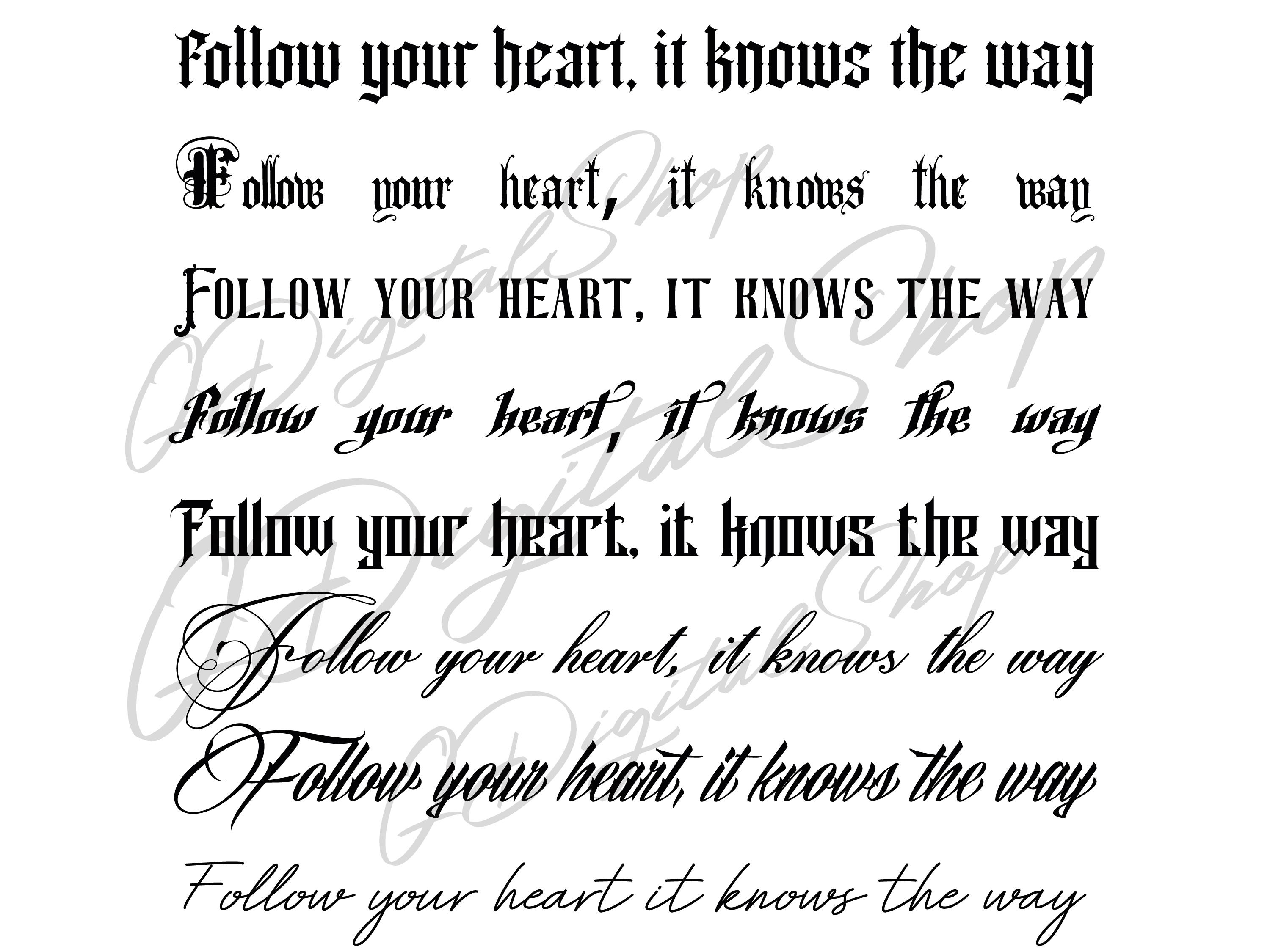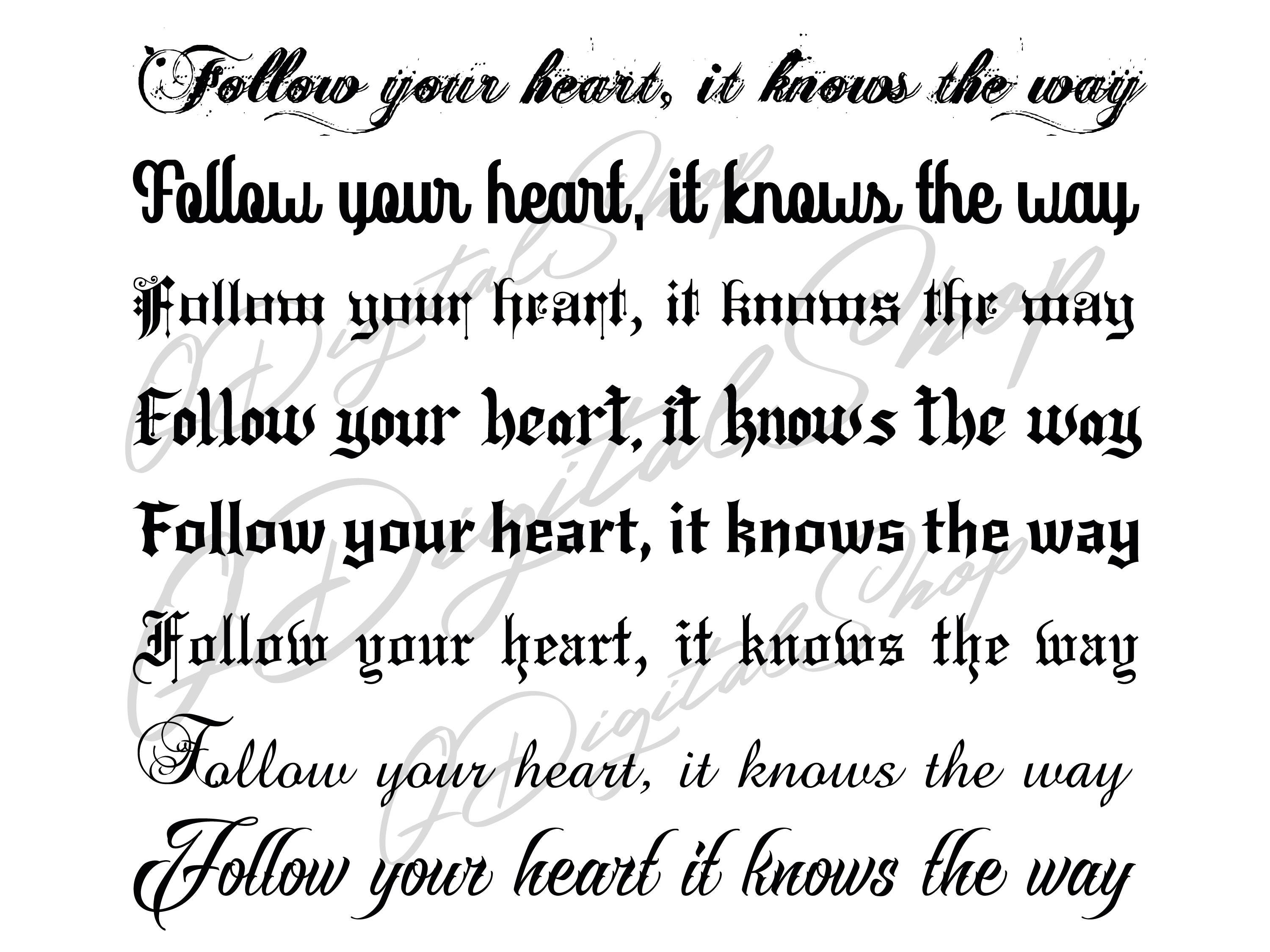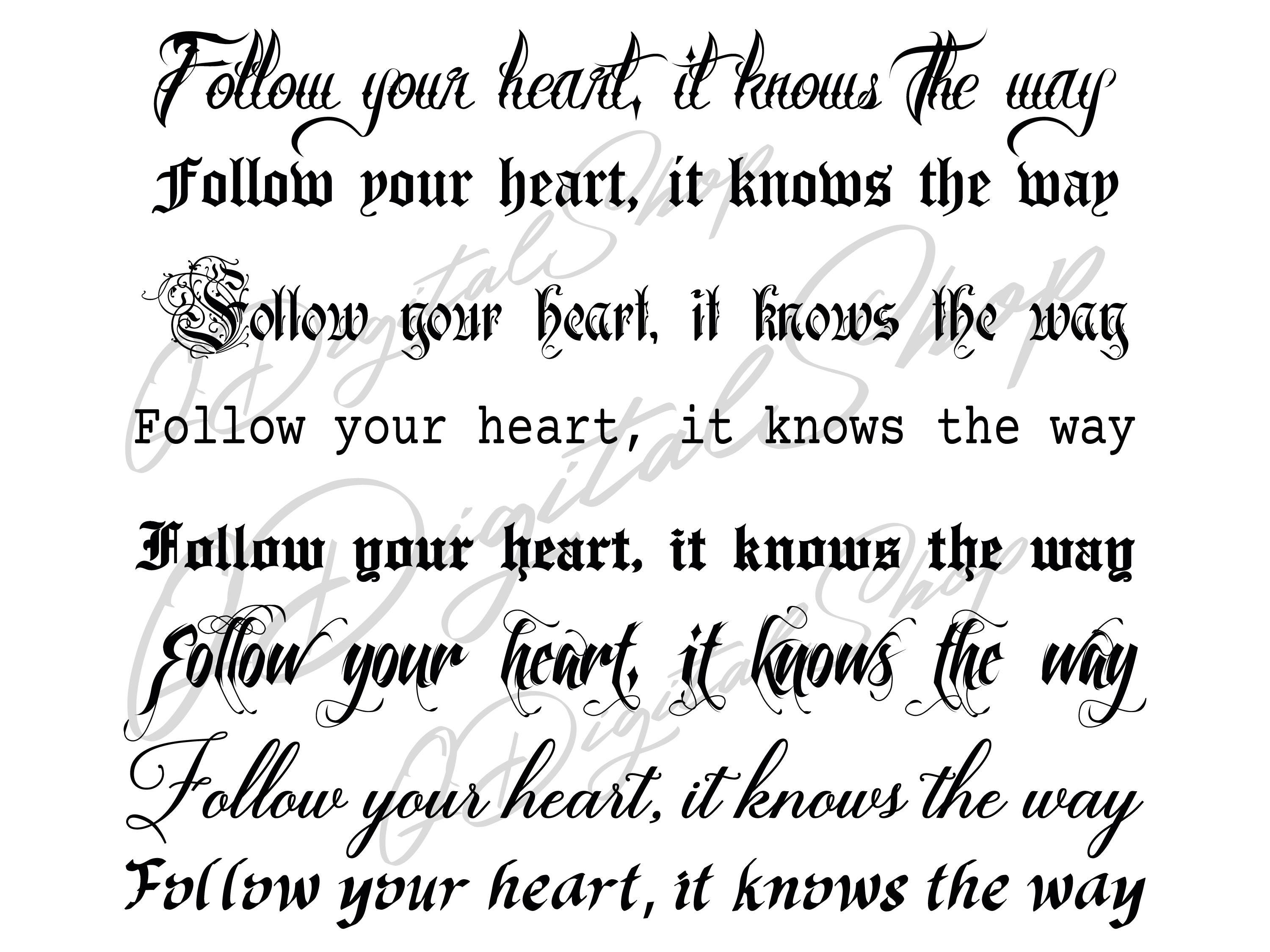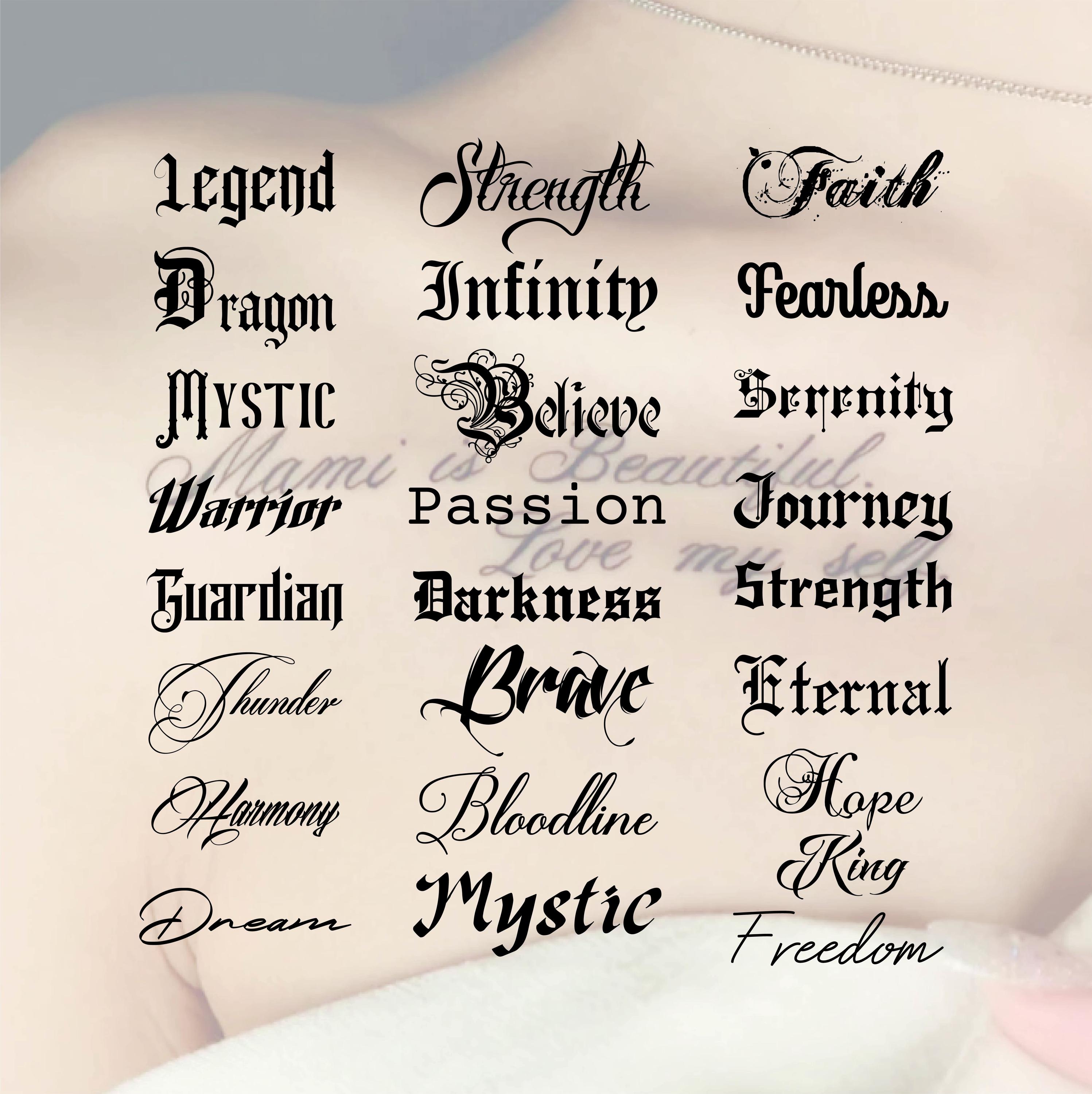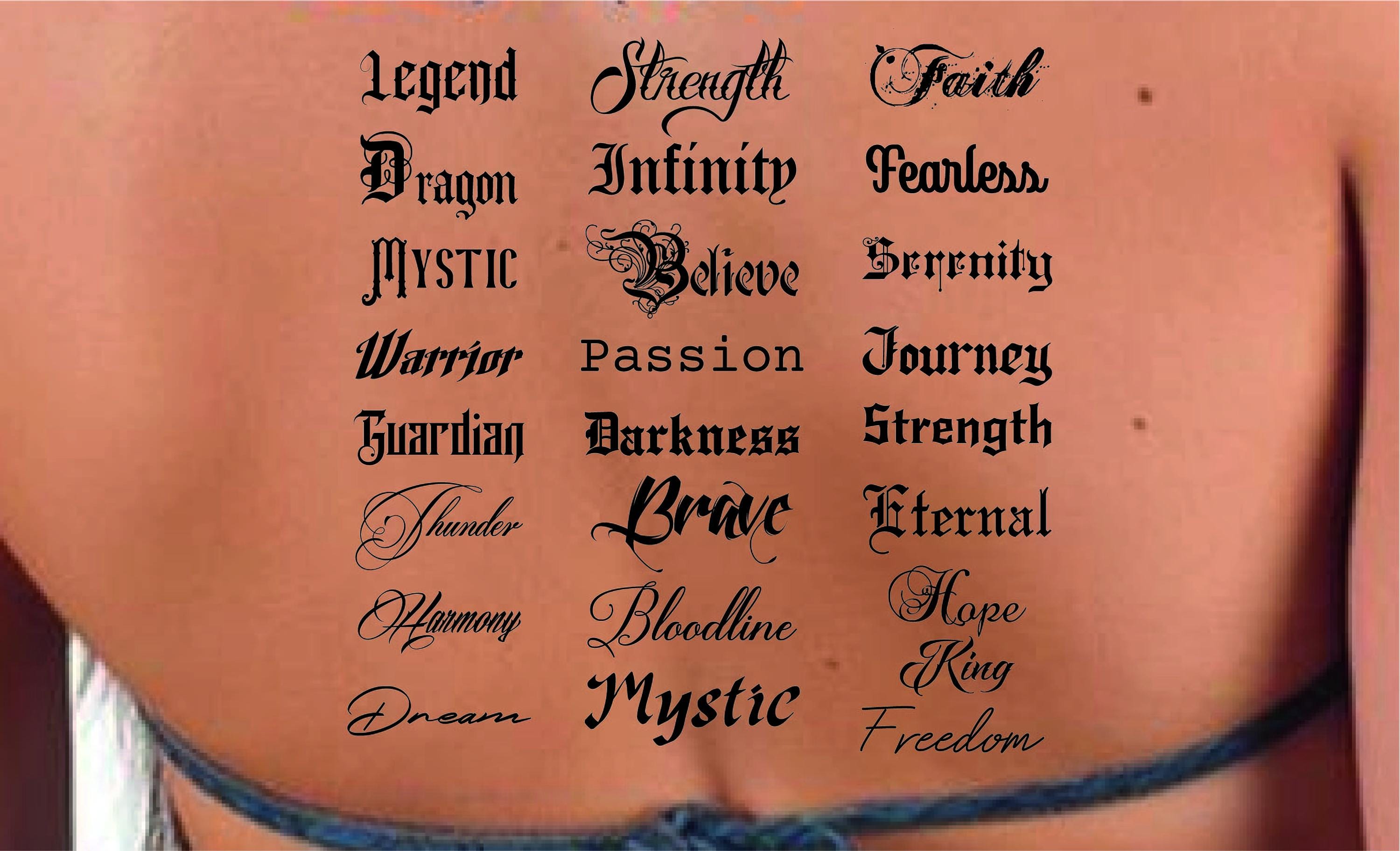
プレミアムタトゥーフォントバンドルで作品をグレードアップ。大胆なクリエイター、タトゥーアーティスト、メーカーのために厳選した、プロ品質のタトゥーフォント24種を収録。クラシックなスクリプトやカリグラフィーから、エッジの効いたモダンレタリングまで、デジタル/フィジカル問わず多彩なプロジェクトで魅力的なデザインを生み出せます。タトゥーフラッシュ、アパレルグラフィック、Cricut用デカール、SNS投稿、ポスター、招待状、ウォールアートなど、いつでもシャープで高品質な仕上がりに。
- プレミアムタトゥーフォント24種:スクリプト、ブラックレター、カリグラフィー、ディスプレイまで多彩に収録。
- クリエイティブな柔軟性:タトゥーアート、アパレル、ステッカー、ポスター、招待状、ブランディングに最適。
- 高いクオリティ:緻密でクリーンな字形により、シャープで洗練された仕上がり。
プロのために作られ、情熱的なクリエイターにも最適なバンドルで、忘れられないレタリングを。